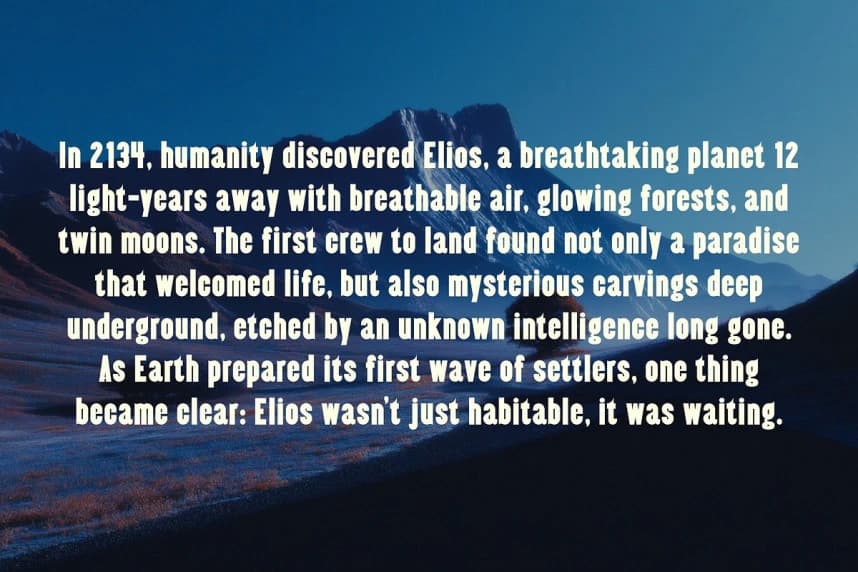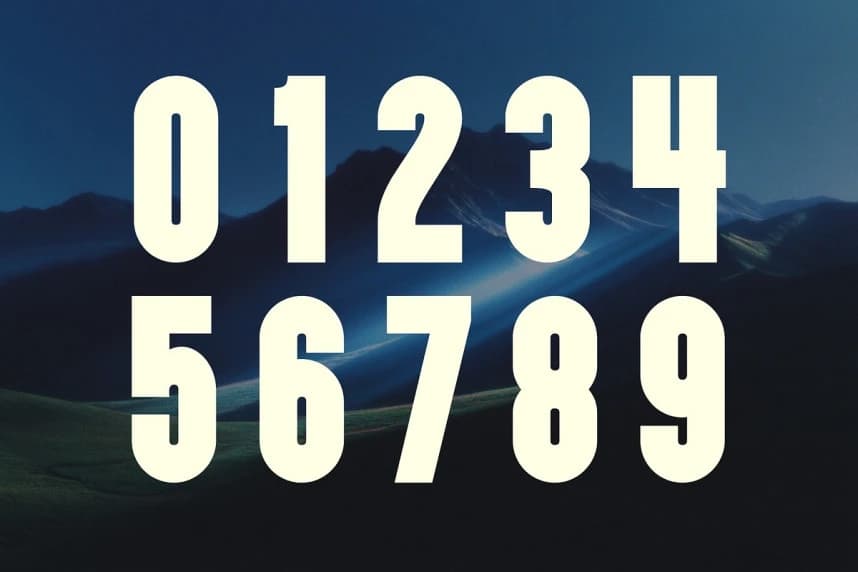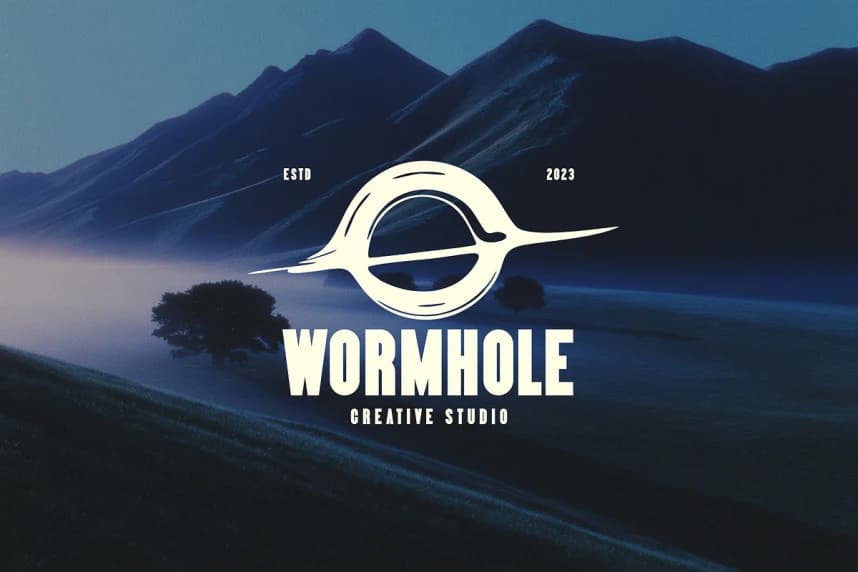
Aventra Font
Aventra Font, güven, açıklık ve minimalist çekiciliği yansıtan uzun bir sans-serif yazı tipidir. Temiz hatları ve rafine geometrisiyle Aventra, markalaşmanızı, ambalajlarınızı ve editoryal projelerinizi zahmetsiz bir zarafetle yükseltmek için tasarlanmıştır.
Aventra Font, özgüven, netlik ve minimalist bir çekicilik yayan uzun bir sans serif yazı tipi. Temiz hatları ve rafine geometrisiyle Aventra, markalaşmanızı, ambalajlarınızı ve editoryal projelerinizi zahmetsiz bir sofistikasyonla yükseltmek için tasarlandı.